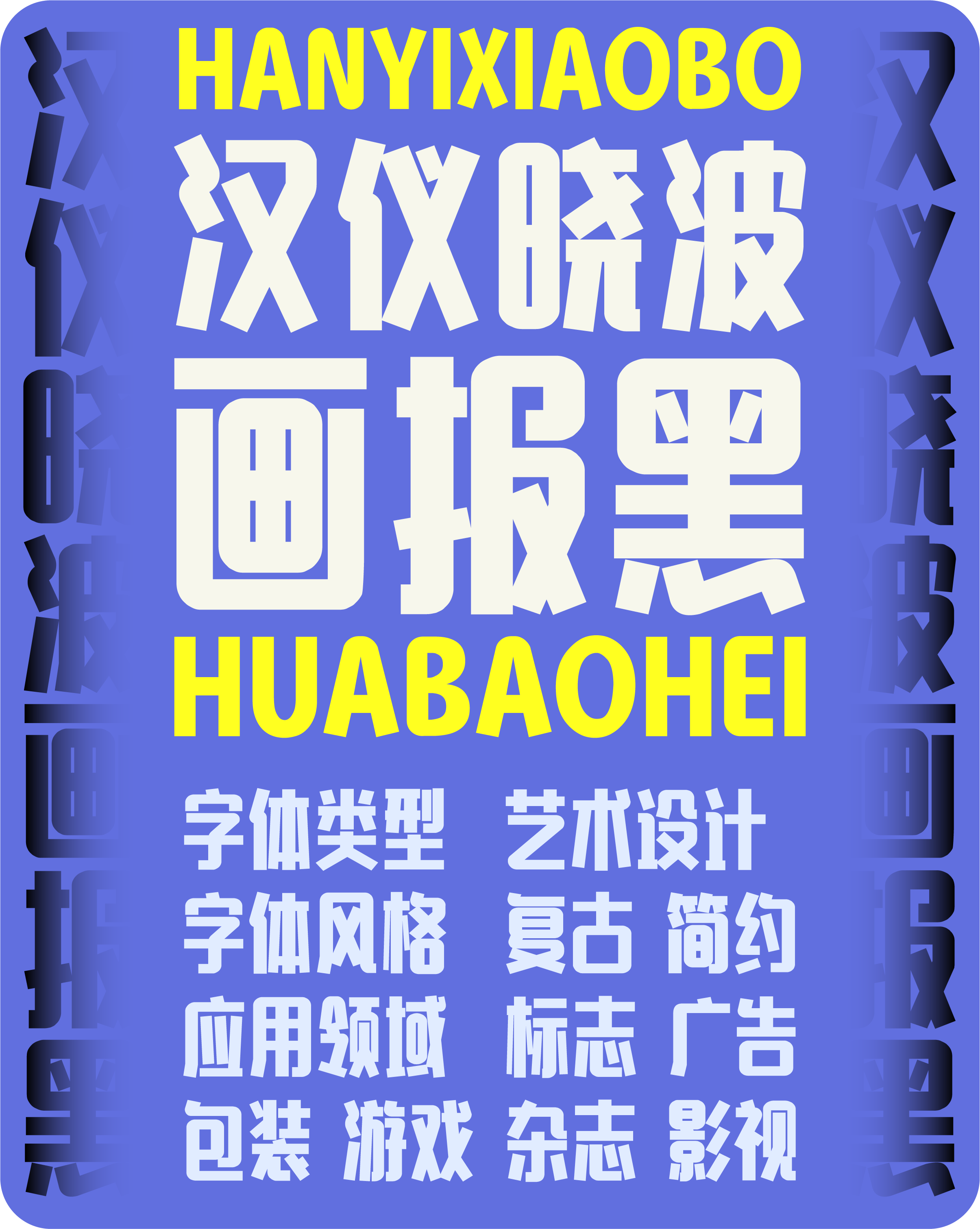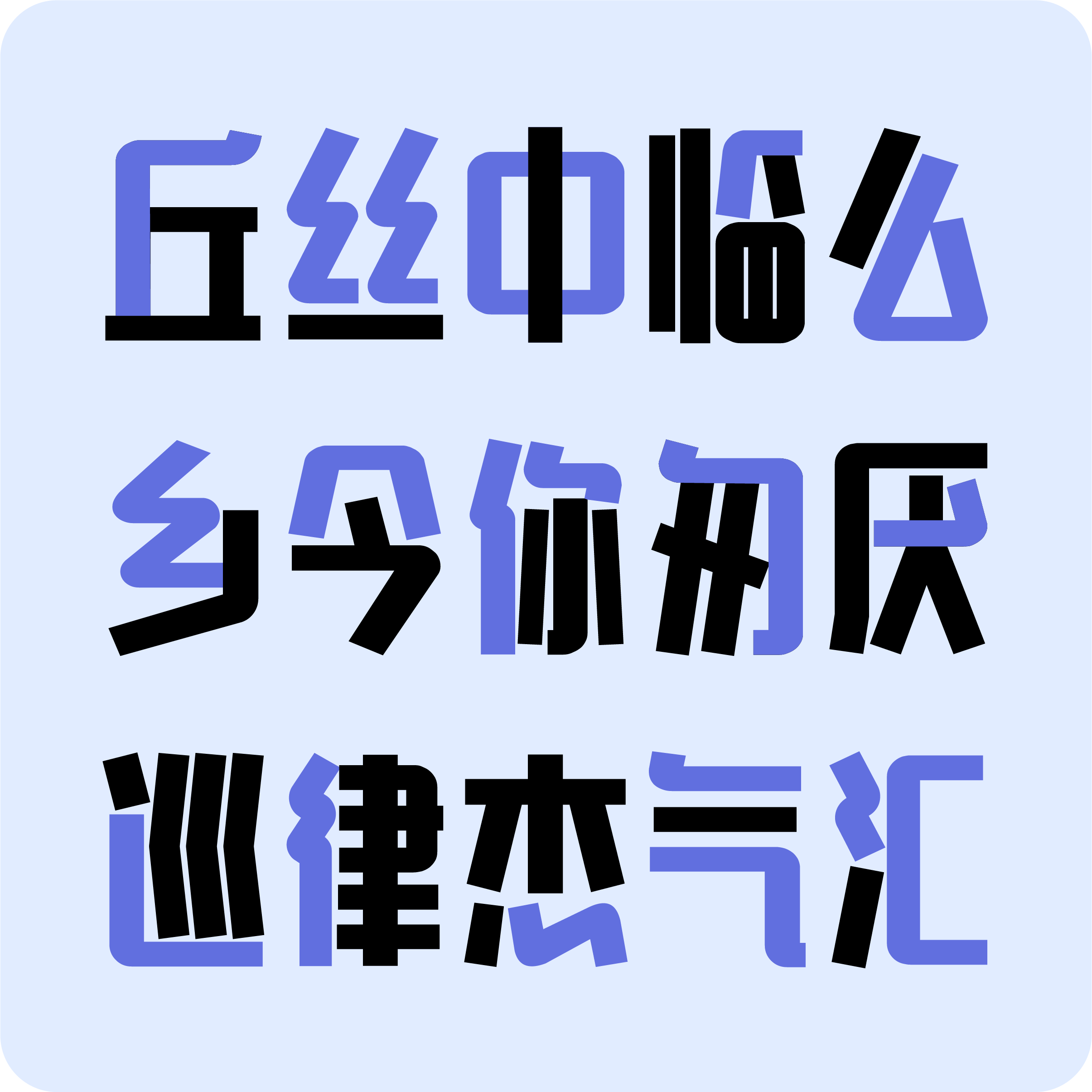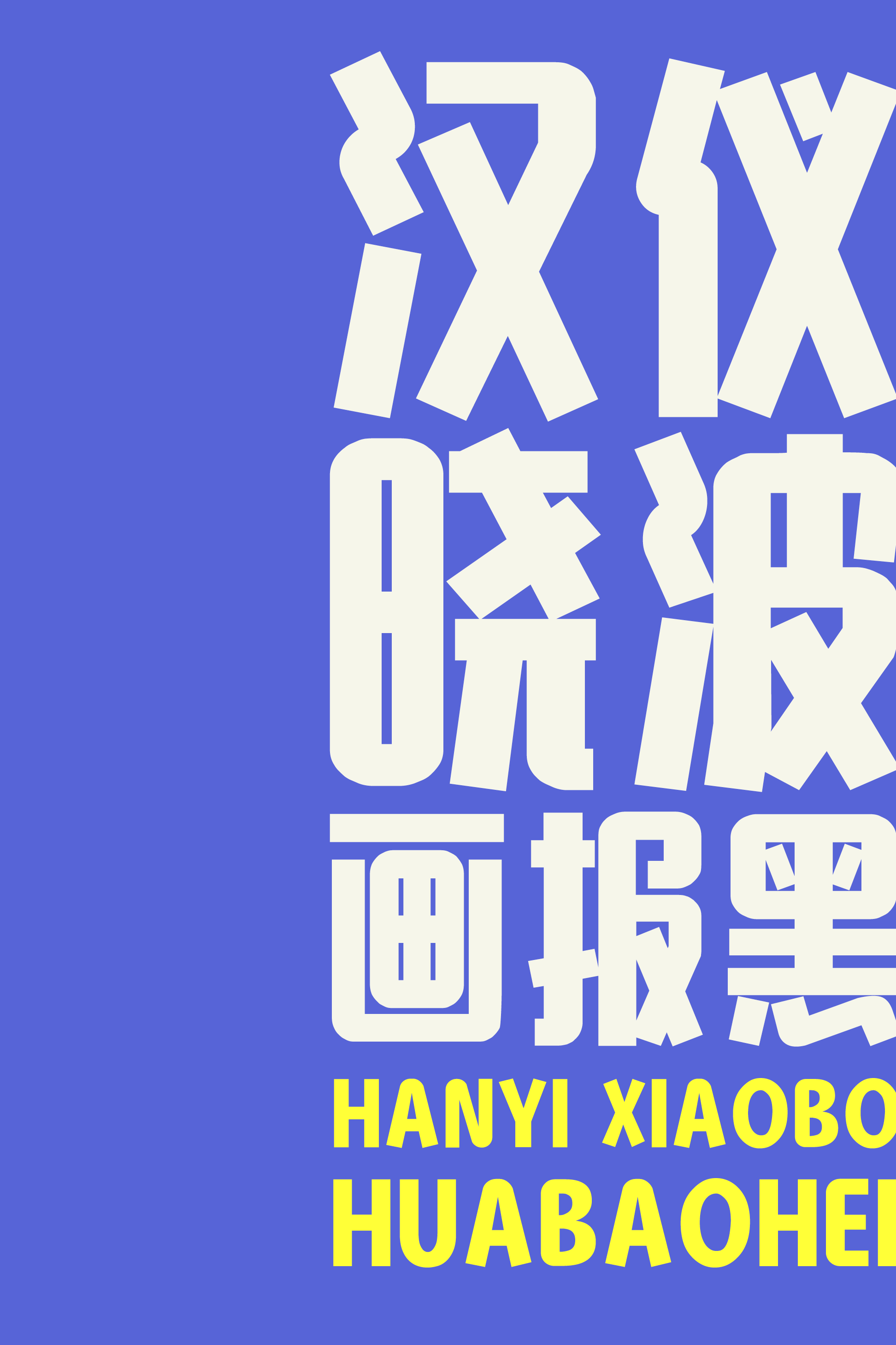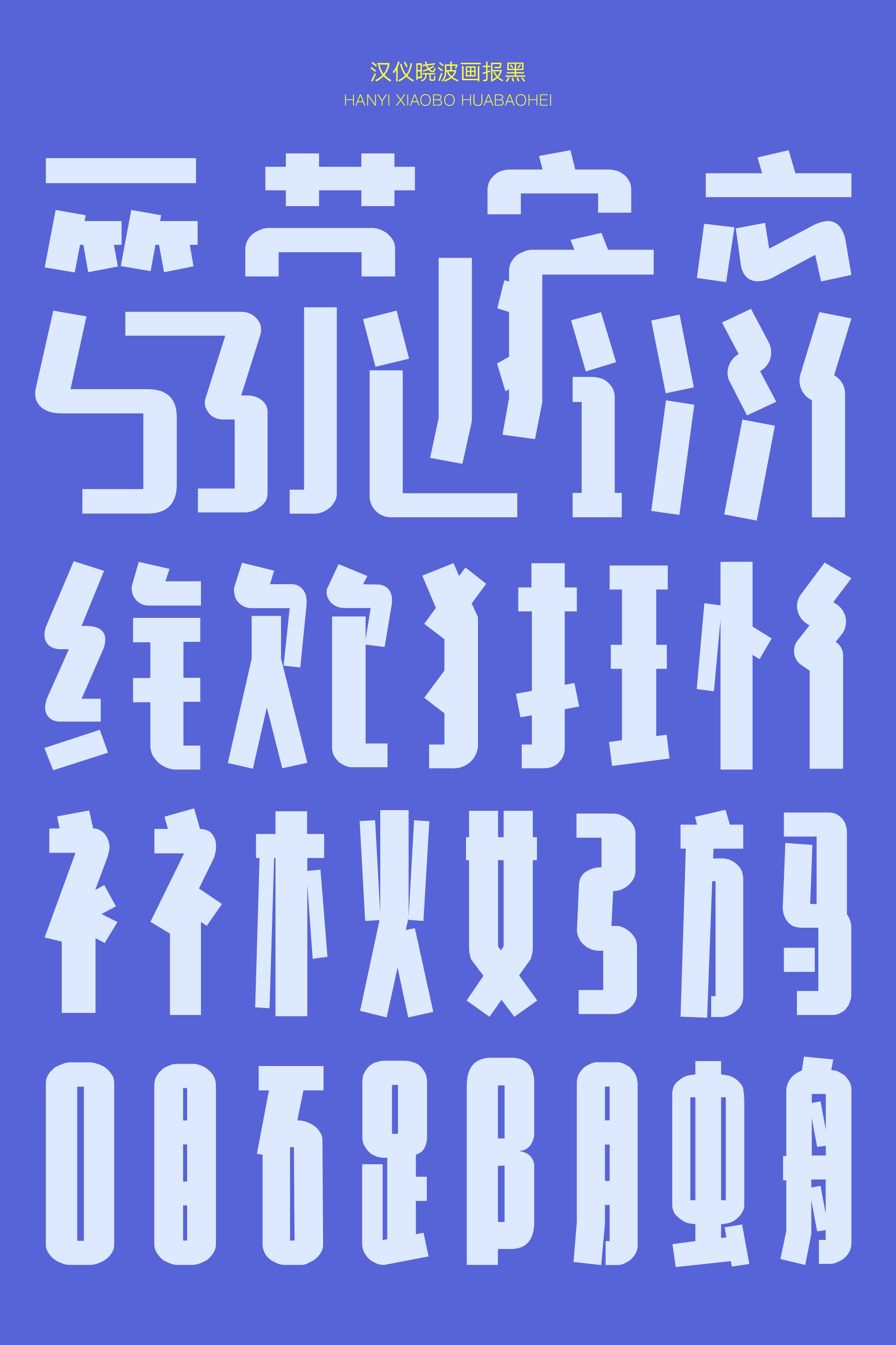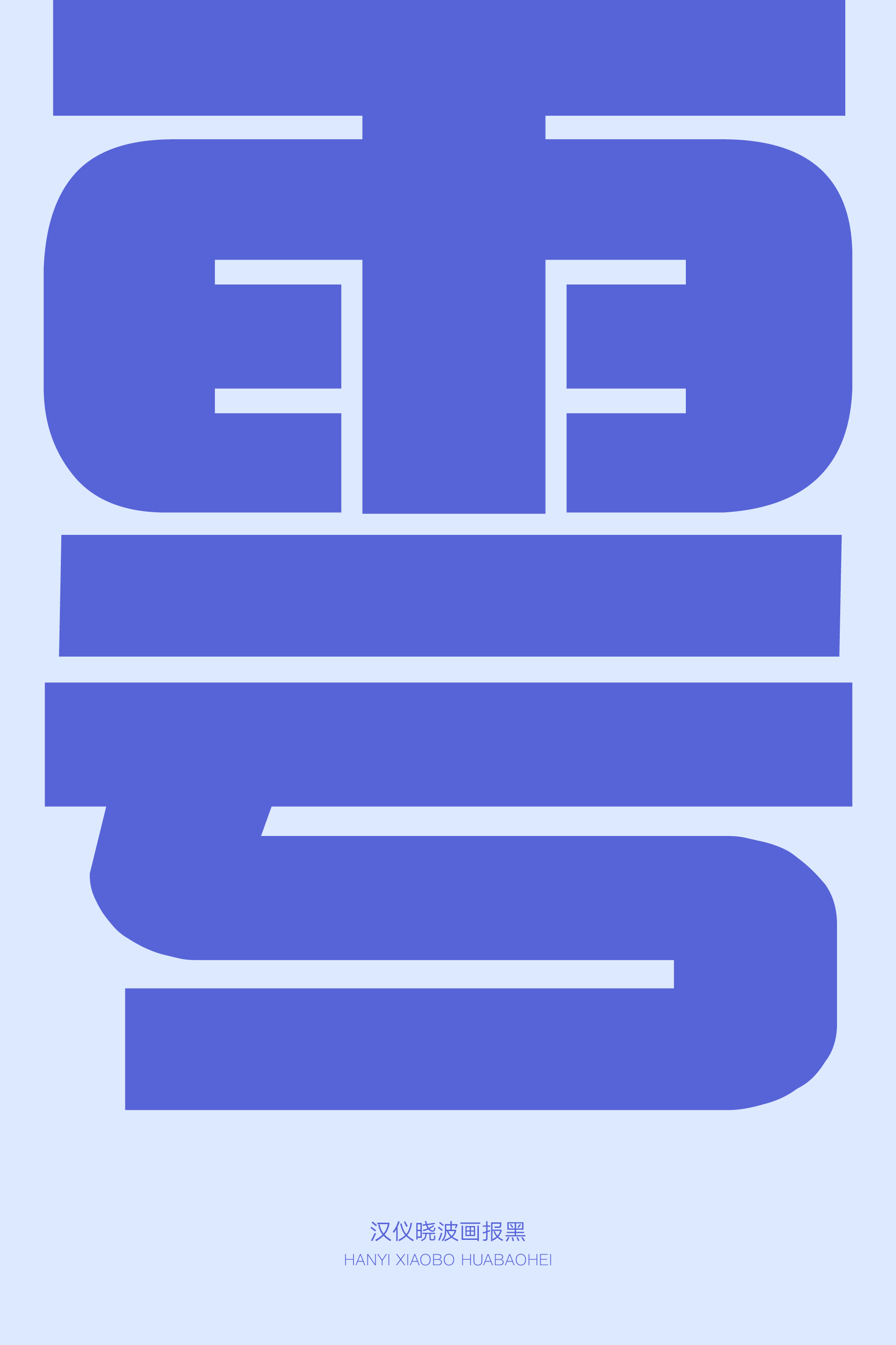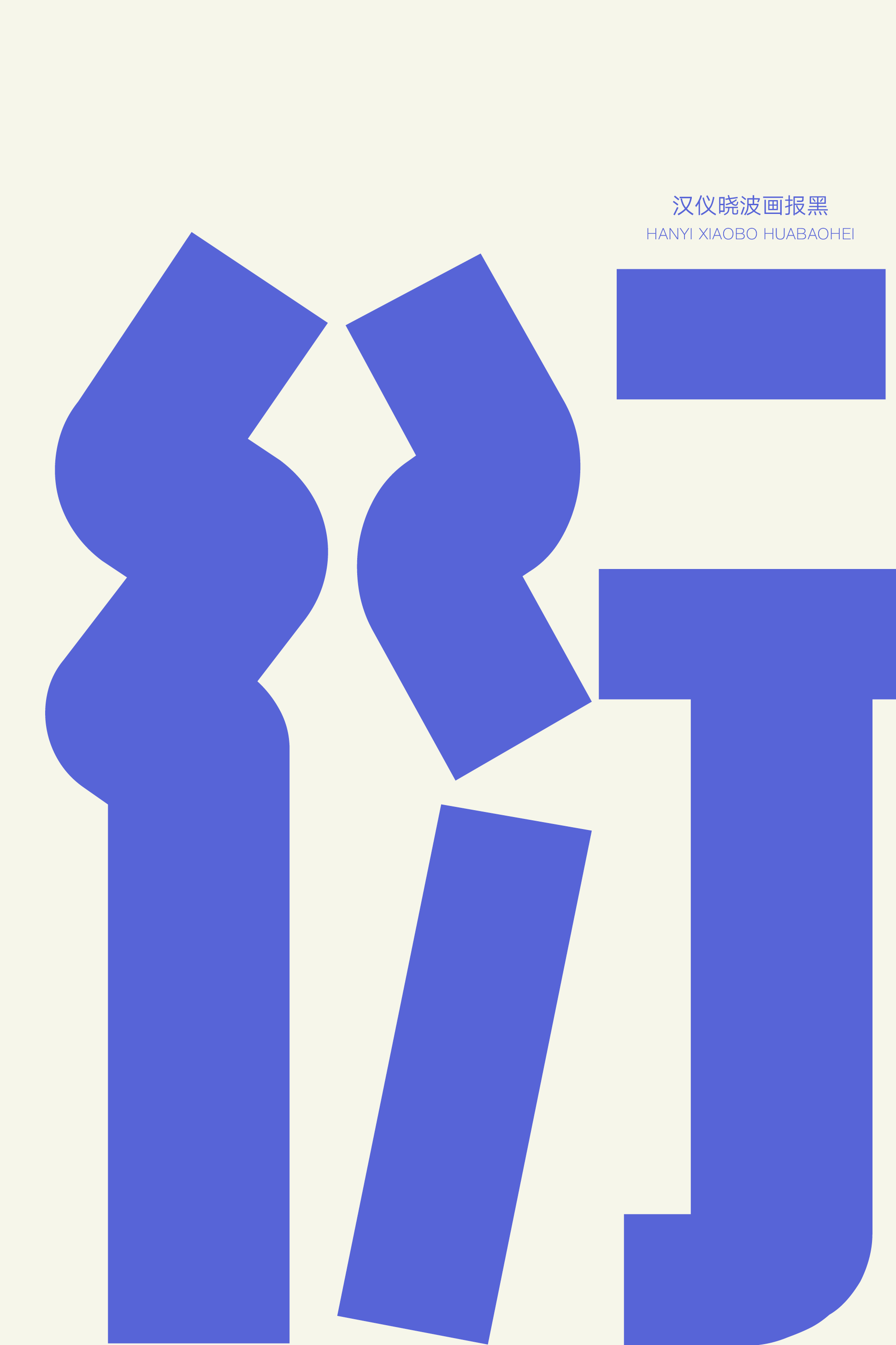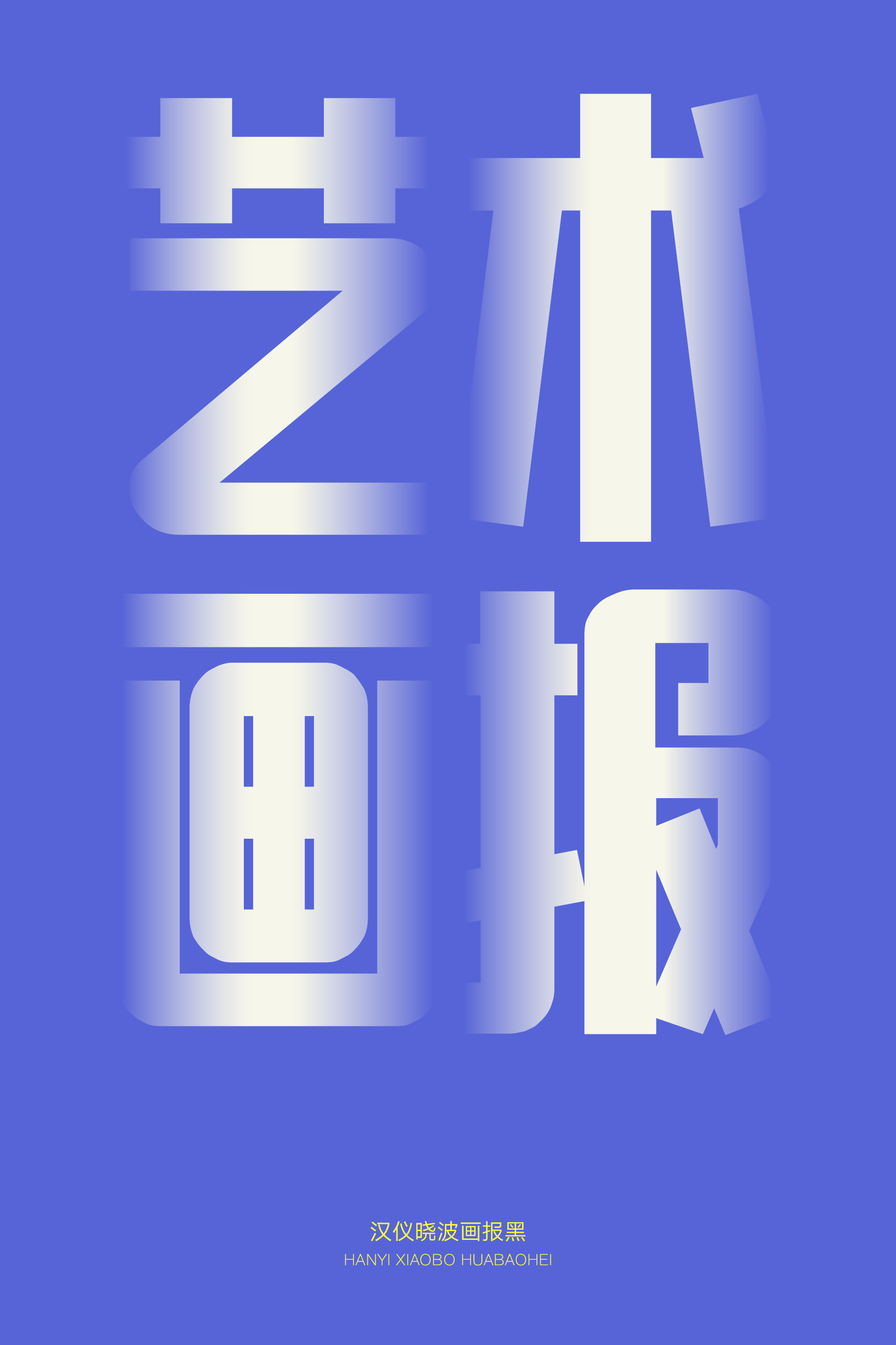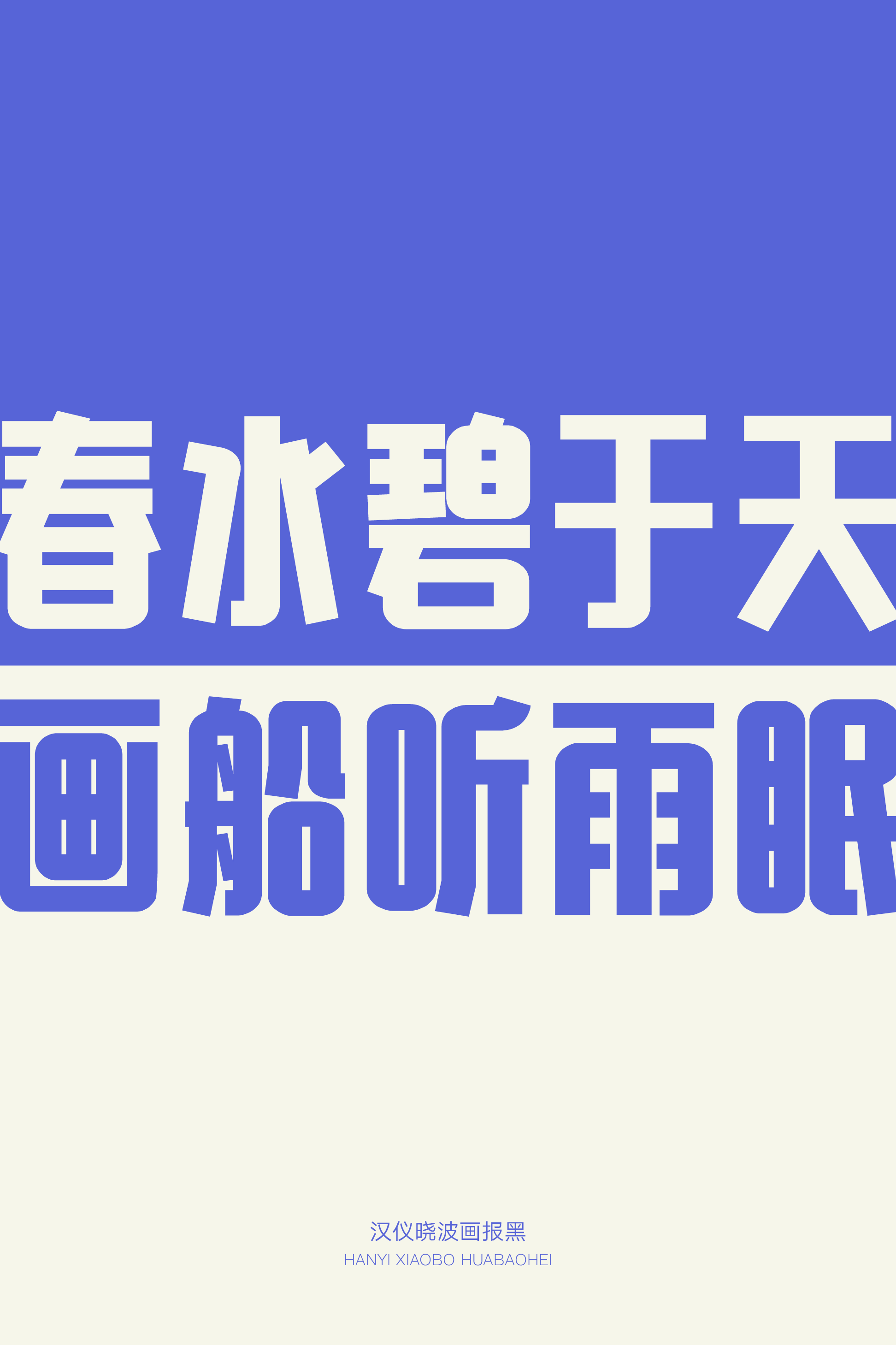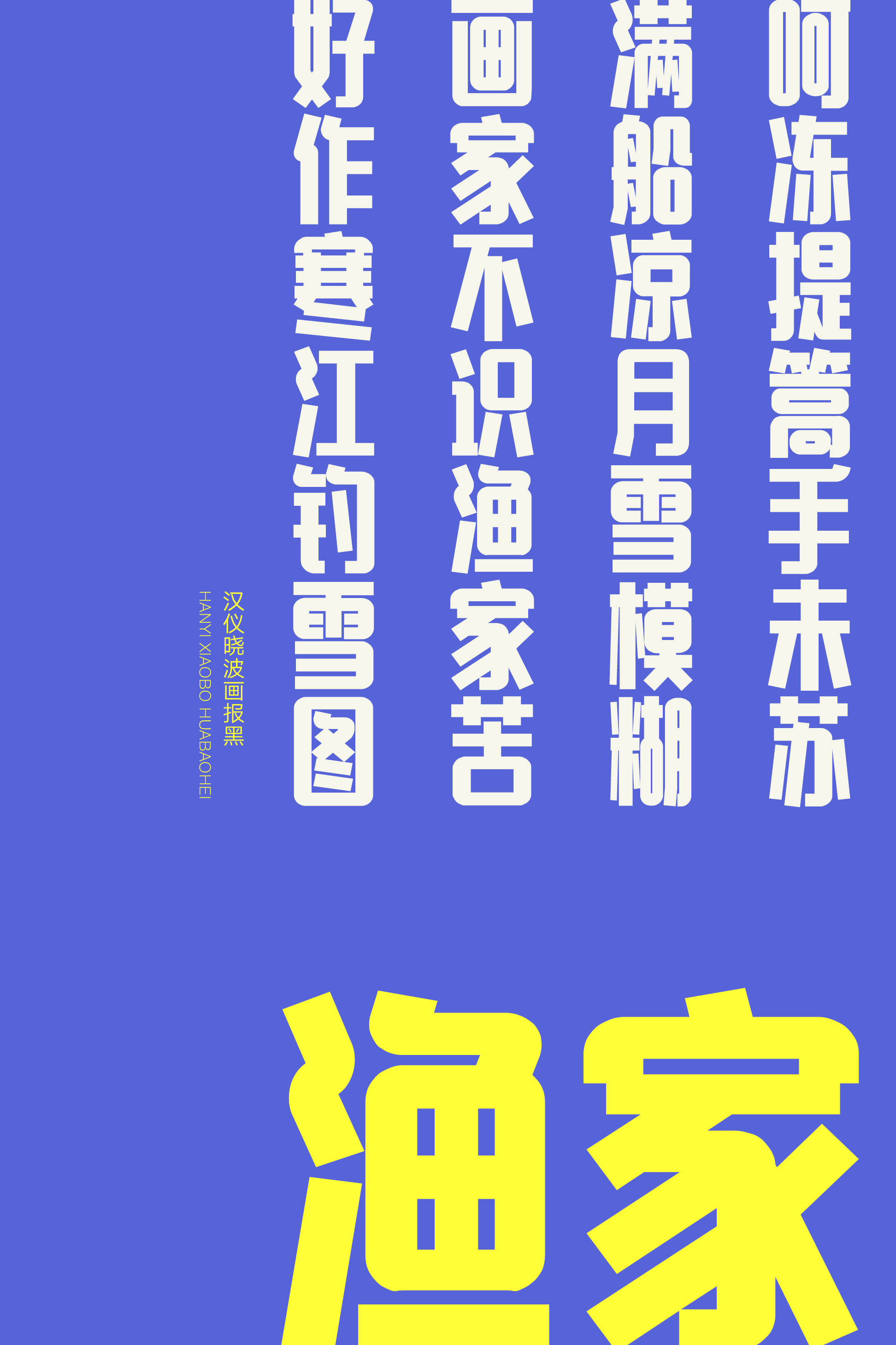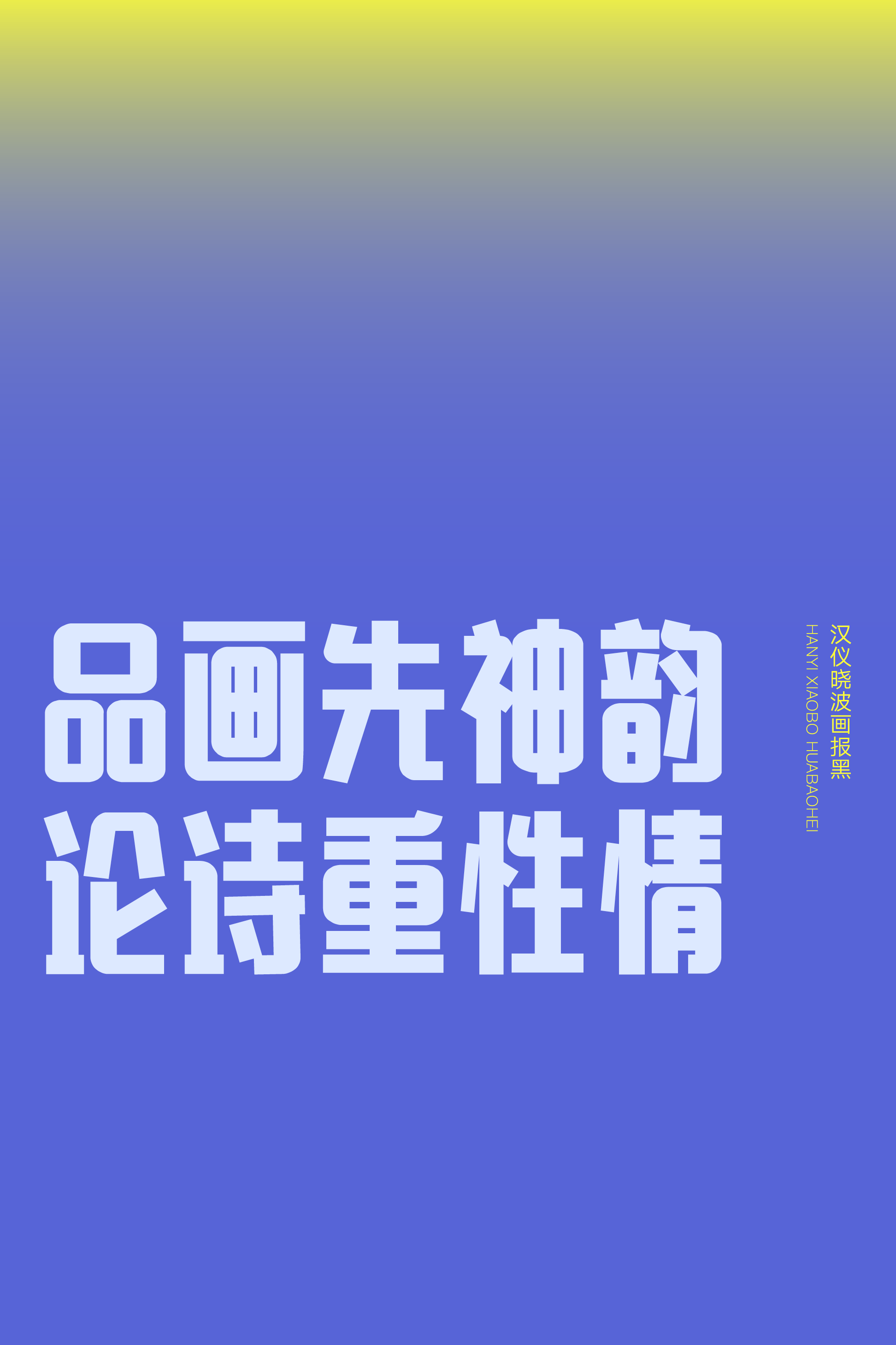
汉仪晓波画报黑
从复古画报中走出来的汉仪晓波画报黑,几何造型感十足的字形呈窄长,等线笔画简约克制,方圆结合,连带自然流畅。这款复古风格的标题字体让设计告别无聊,在整齐的排版效果中趣味满满,适用于品牌包装、电商广告、报刊杂志、影视游戏等多种使用场景。
字形为窄长的圆角矩形。
简约的等线笔画方圆结合:横平竖直、撇捺克制、转折圆滑。
笔画连带自然流畅。
西文部分保留窄长的字形,方圆结合,简约流畅。